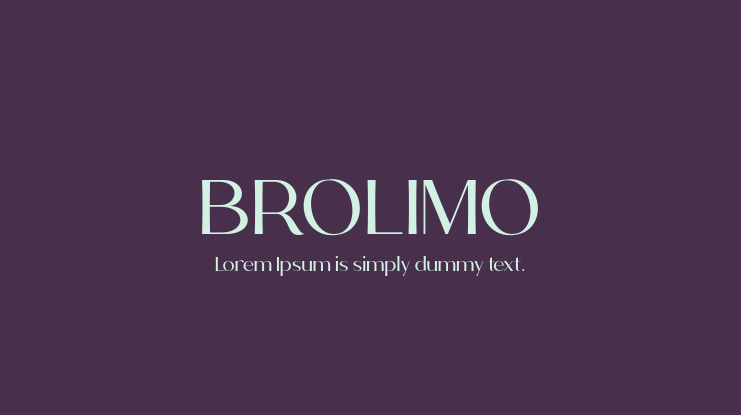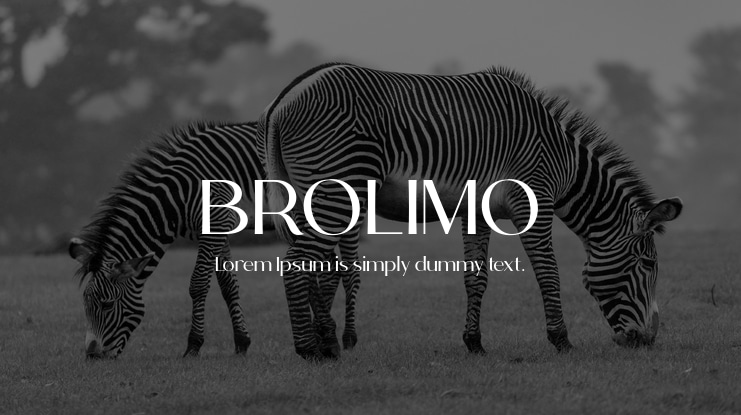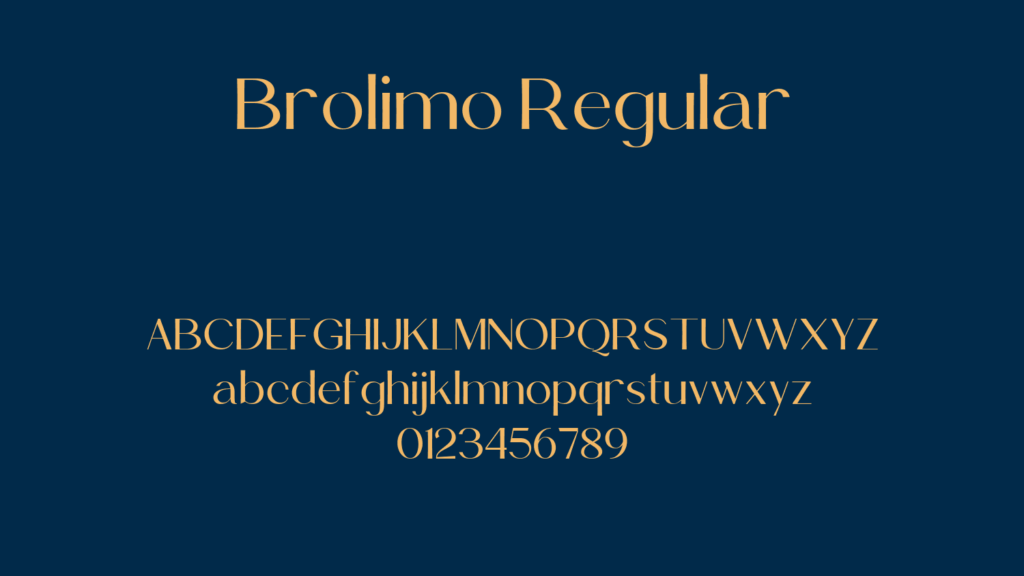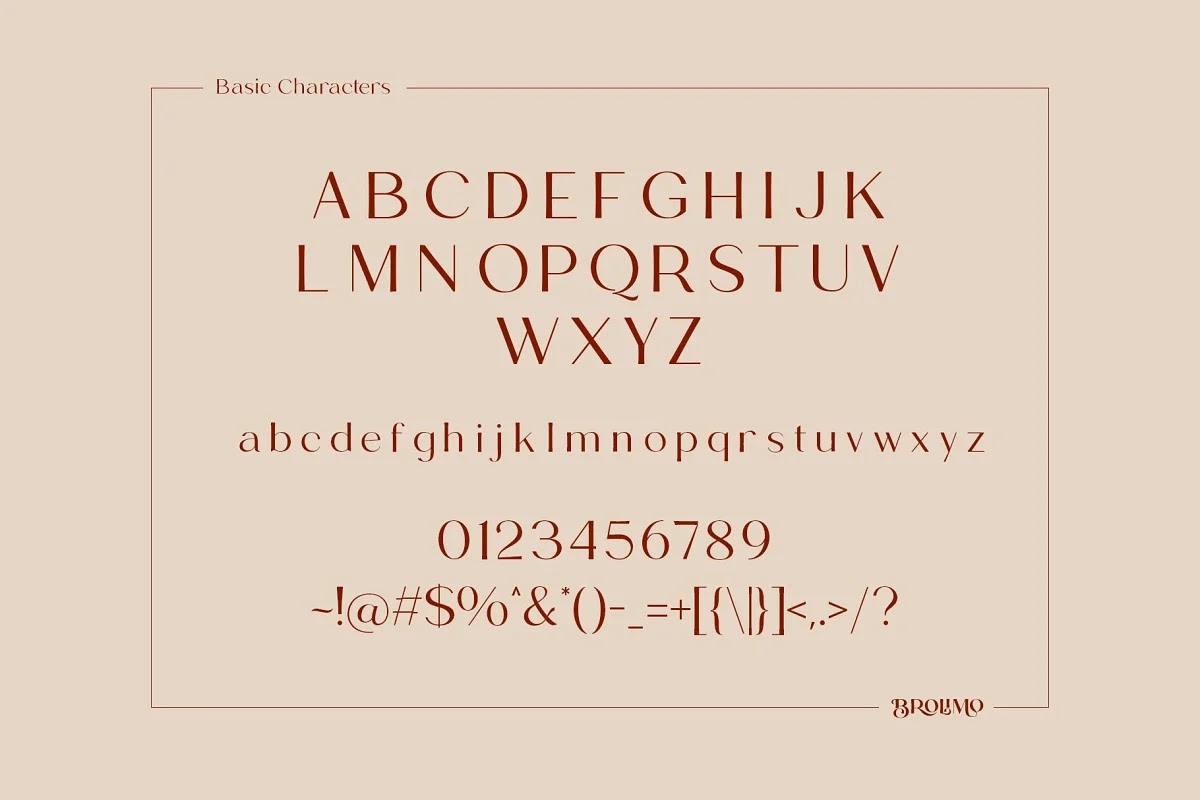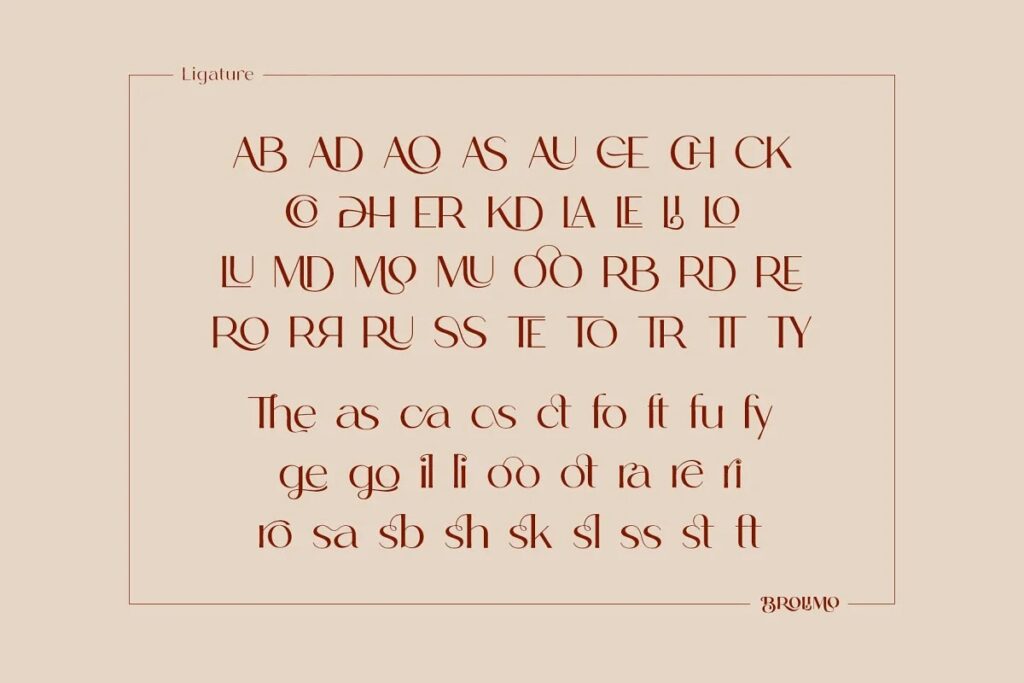
Font Brolimo Việt hóa là bộ phông chữ thuộc dòng Modern Serif mang đậm phong cách tạp chí thời trang cao cấp với các đường nét thanh đậm tương phản sắc nét và cấu trúc hình học kiêu sa. Với vẻ ngoài lịch lãm, hiện đại và đậm tính nghệ thuật, kiểu chữ này giúp các kiến trúc sư, nhà thiết kế nâng tầm thẩm mỹ cho các bản vẽ phối cảnh biệt thự nghỉ dưỡng, sảnh đón tiếp khách sạn boutique hay bìa hồ sơ năng lực dự án.
Tỷ lệ thanh lịch và độ tương phản sắc sảo của font Brolimo Việt hóa
Điểm cuốn hút của Font Brolimo Việt hóa nằm ở sự đối lập nhịp nhàng giữa các nét đứng dày dặn và nét ngang thanh mảnh như sợi chỉ, kết hợp cùng các chi tiết bo cong hình elip đầy duyên dáng. Tỷ lệ các ký tự được căn chỉnh theo chuẩn mực của phong cách thiết kế đương đại, mang lại cảm giác thoáng đạt và quý phái cho từng dòng tiêu đề.
Sự ổn định về mặt thị giác của dòng font này tạo nên phong thái trang nhã, tin cậy và khẳng định đẳng cấp riêng biệt. Khi xuất hiện trên các bề mặt vật liệu kiến trúc sang trọng như đá cẩm thạch trắng, inox mạ vàng xước hay kính cường lực phản quang trong các công trình nhà lắp ghép cao cấp, Brolimo tạo nên điểm nhấn thị giác cuốn hút.
| Phân loại phong cách | Modern Serif / Editorial Display / High-contrast |
| Mục đích phù hợp | Biển tên villa cao cấp, bìa hồ sơ năng lực, logo |
Tư vấn từ chuyên viên: Brolimo sở hữu các nét thanh mảnh và độ tương phản rất lớn. Để bản thiết kế đạt hiệu quả thẩm mỹ tốt, bạn nên sử dụng phông chữ này cho các tiêu đề chính, tên dự án hoặc câu slogan ngắn ở kích thước lớn. Phần nội dung mô tả kỹ thuật chi tiết nên đi kèm một phông chữ không chân thanh mảnh hơn để người xem tiếp nhận thông tin dễ dàng.
03 Ứng dụng phông chữ Brolimo vào công trình thực tế
Nhờ vẻ ngoài quý phái và tính thẩm mỹ cao cấp, bộ phông chữ này mang lại giá trị thực tế lớn trong khâu tạo điểm nhấn cho các công trình hiện đại:
- Biển hiệu mặt tiền cho Villa và Khu nghỉ dưỡng Boutique: Những nét chữ thanh lịch của Brolimo rất ăn ý khi gia công chữ nổi bằng inox vàng gương hoặc khắc chìm trên đá hoa cương, giúp căn nhà lắp ghép nghỉ dưỡng toát lên vẻ đài các và thu hút sự chú ý của du khách.
- Bìa hồ sơ năng lực dự án kiến trúc: Sử dụng tải font Việt hóa Brolimo cho tên dự án và tiêu đề các chương mục giúp hồ sơ trông như một ấn phẩm tạp chí danh giá, thể hiện gu thẩm mỹ tinh tế và năng lực của đơn vị kiến tạo.
- Hệ thống biển tên phòng và bảng chỉ dẫn nội khu: Phông chữ này khi in trên kính mờ hoặc kim loại phủ sơn tĩnh điện sẽ giúp không gian sảnh đón tiếp và hành lang toát lên chất nghệ thuật thanh lịch.
03 Lưu ý bố cục font Việt hóa Brolimo luôn sang trọng và rõ nét
Để khai thác hiệu quả vẻ đẹp của dòng font thời trang quý tộc này mà không làm ảnh hưởng đến khả năng đọc của bản vẽ, người thiết kế nên lưu tâm một số kinh nghiệm sau:
- Tránh sử dụng ở kích thước quá nhỏ: Do có các nét thanh mảnh như sợi chỉ, Brolimo hiển thị đẹp ở kích thước chữ từ 16pt trở lên trong in ấn. Ở kích thước quá nhỏ, nét thanh có thể bị mờ nhòe do độ mịn của chất liệu giấy in.
- Nới rộng khoảng cách ký tự: Đối với các tiêu đề viết hoa toàn bộ, việc kéo giãn nhẹ khoảng cách giữa các chữ cái sẽ làm tăng tính trang nghiêm, giúp bố cục thông thoáng và mang đậm phong thái kiến trúc đương đại.
- Bố trí nền màu đơn sắc tương phản: Brolimo phát huy hiệu quả thị giác cao khi đặt trên các nền màu đơn sắc có chiều sâu như đen tuyền, trắng ngọc trai, xám than hoặc xanh rêu sẫm, giúp các đường nét sắc sảo của bộ chữ được tôn vinh rõ ràng.
FAQs – Thắc mắc thường gặp khi sử dụng phông chữ Brolimo
1. Font Brolimo có dùng được trên ứng dụng Canva không?